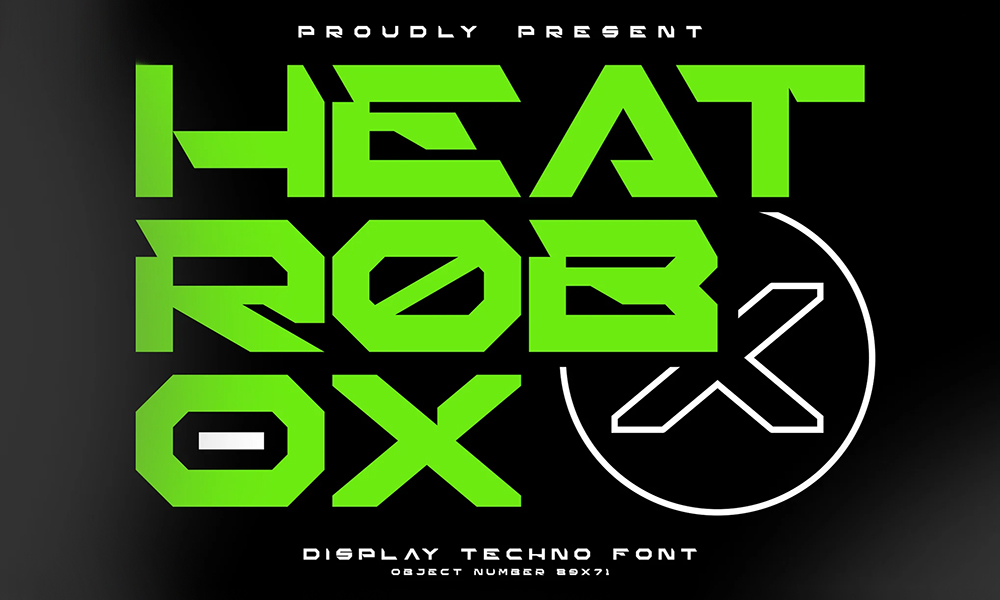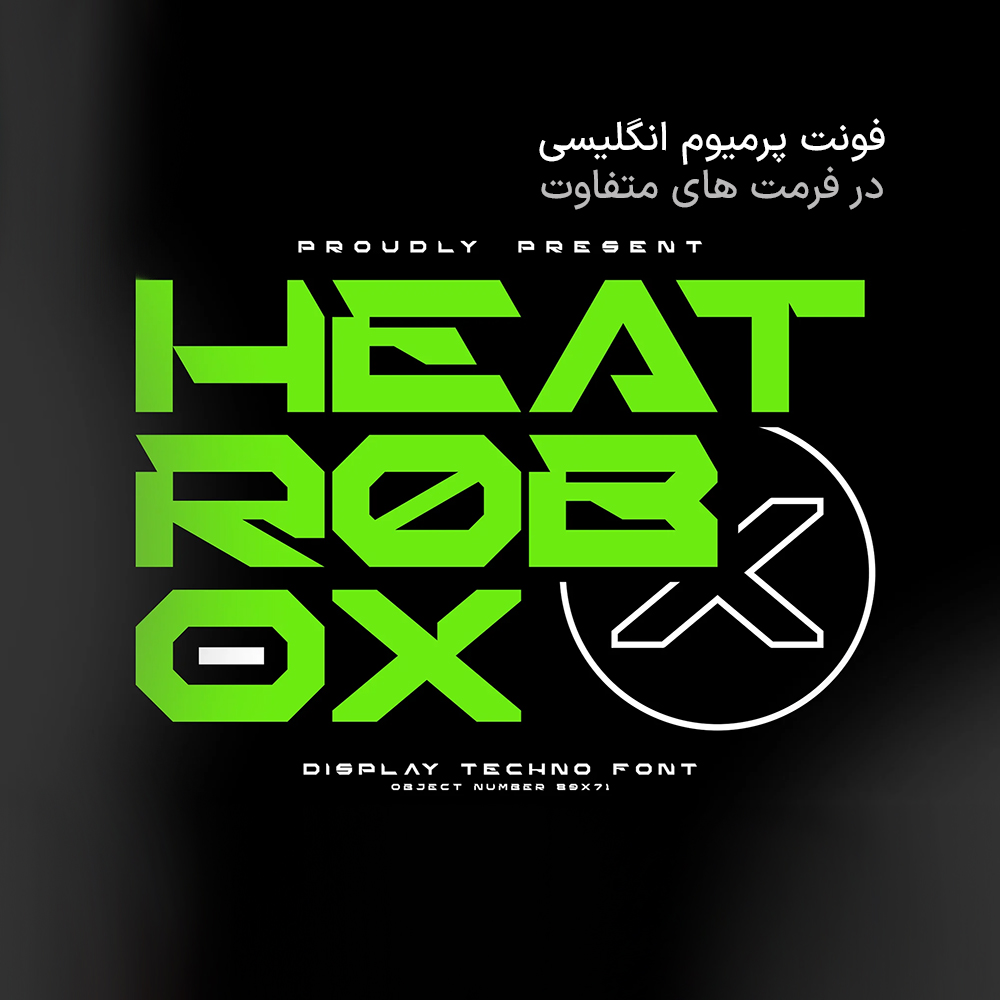
فونت پرمیوم و انگلیسی Heat Robox یک فونت نمایشی آیندهنگر جسورانه و پیشرو که برای آوردن لبهای از فناوری پیشرفته، سایبرنتیک و علمی تخیلی به پروژههای شما طراحی شده است.
فونت Heat Robox با زوایای تیز، هندسه براق و زیباییشناسی دیجیتال مدرن خود، برای برندسازی فناوری، بازی، ورزشهای الکترونیکی، عناوین فیلمهای علمی تخیلی و طرحهای نوآورانه ایدهآل است.